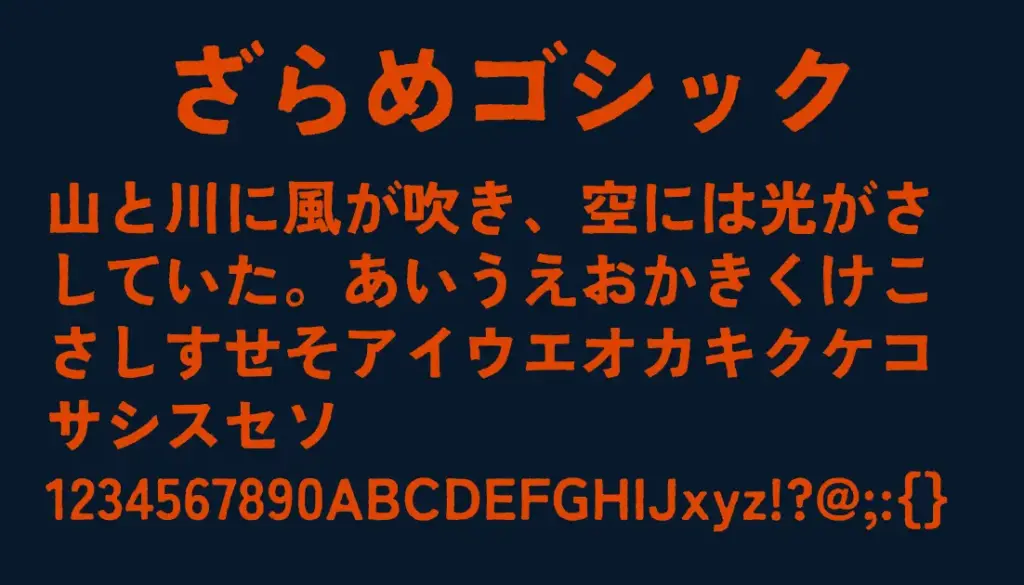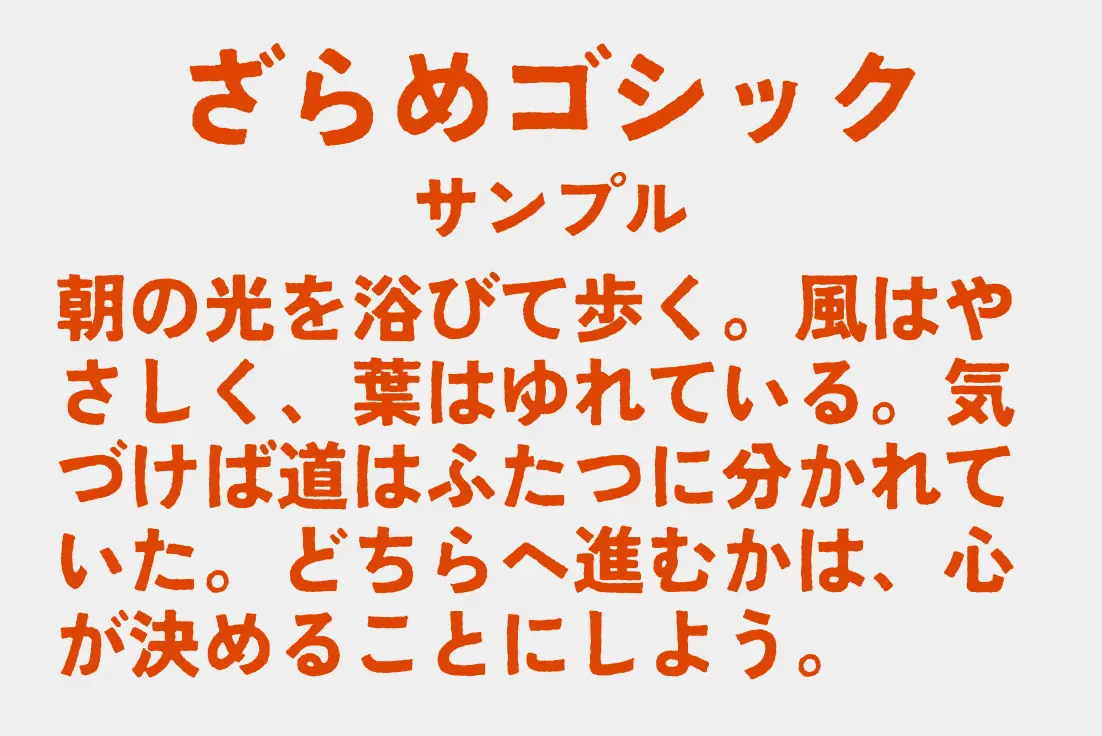
Zen角ゴシックA をベースに「墨だまり」や「ラフな質感」を加えて手がけられた和文ゴシックフォント。力強くザラついたストロークが特徴で、タイトルやロゴなど“雰囲気・インパクト重視”のデザインに向いています。少し荒削りな質感が手描き風の味わいを出すため、動画用バナーやポップなサムネ、アイキャッチなどにもぴったりです。
ざらめゴシック